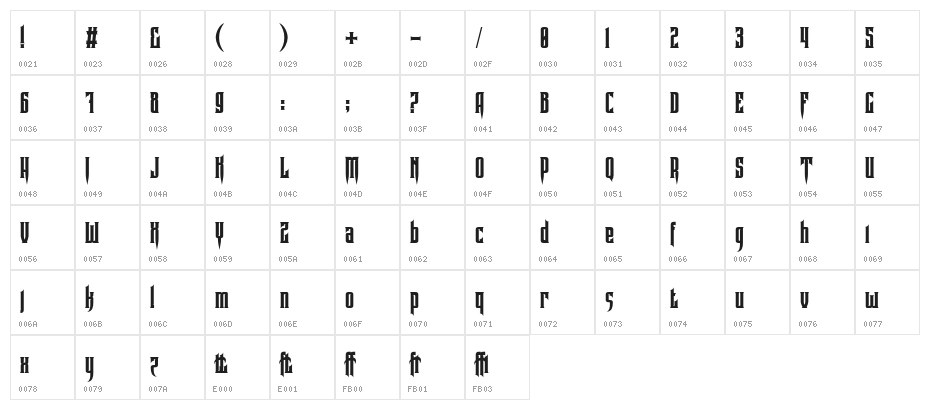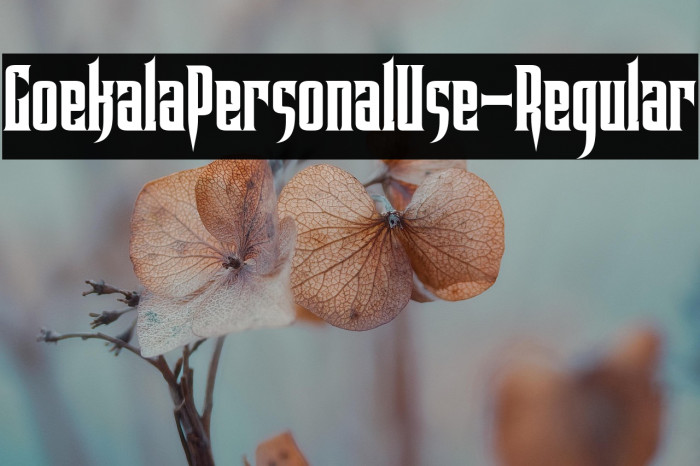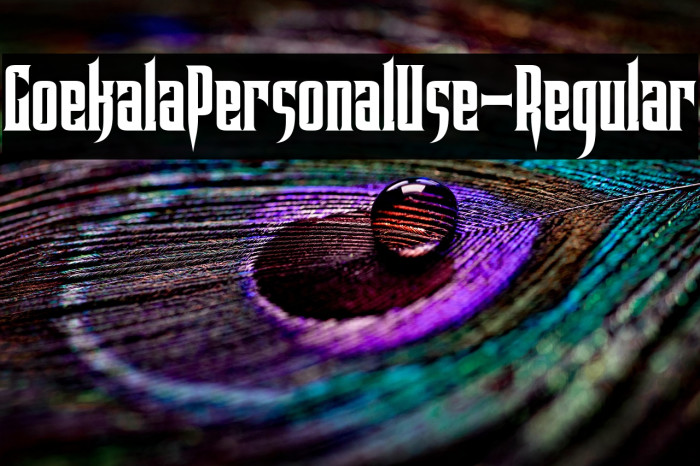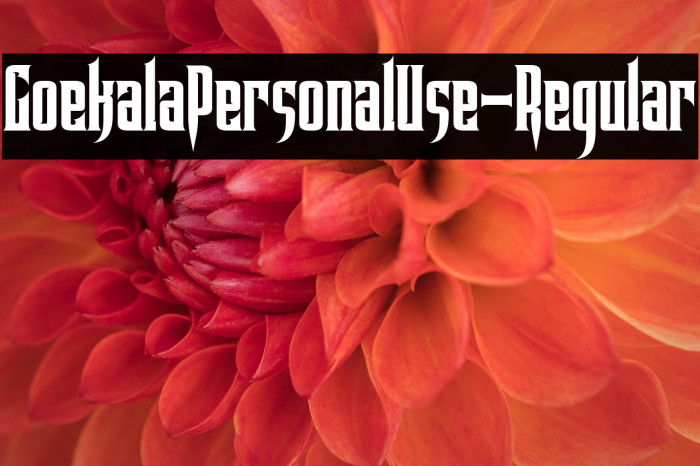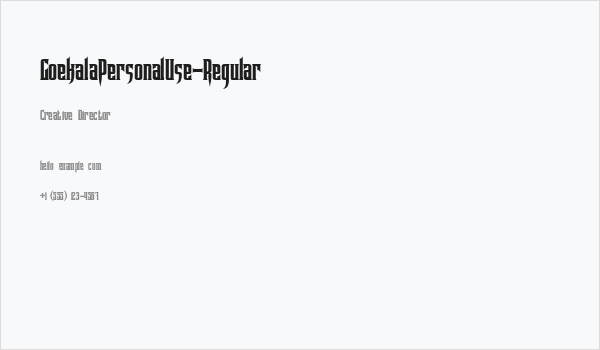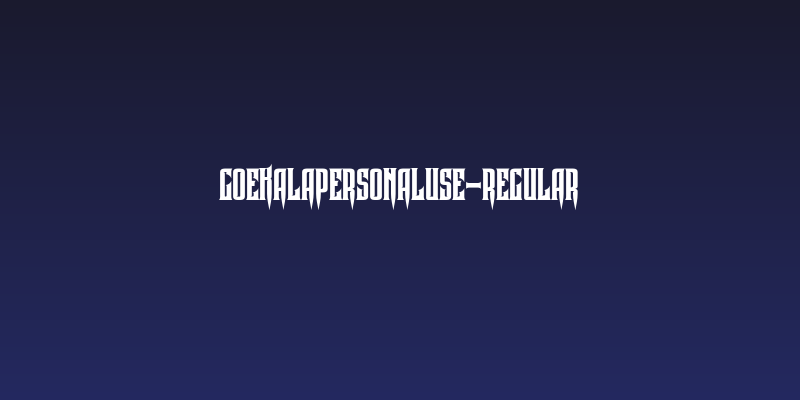
GoekalaPersonalUse-Regular Font
| Stile generale | Gothic, Dramatic |
| Caso d'uso | Logos, Posters, Headlines |
| Progetti proposti | Ideal for fantasy-themed designs, band logos, posters, and video game titles. |